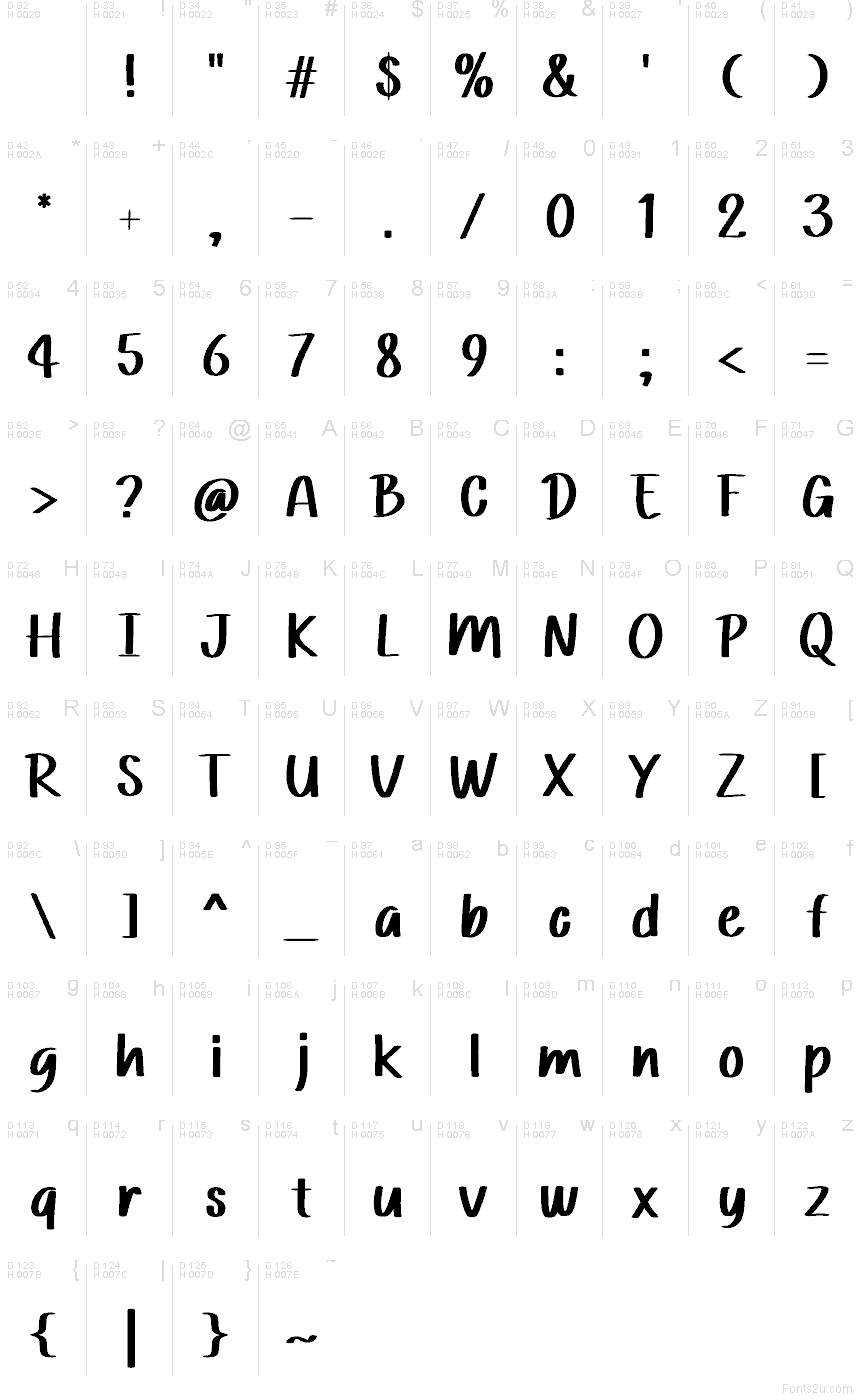
Border Wall від Hello Good Studio - це безкоштовний рукописний шрифт із високими, плавними штрихами та каллиграфічним характером. Літери вирізняються виразним контрастом між широкими вигинами та тонкими з'єднаннями, а м'які, округлі форми надають тексту природного, ритмічного вигляду.
Border Wall чудово підходить для створення логотипів, заголовків на плакатах, пакування, графіки з цитатами та редакційних акцентів, де потрібен рукописний стиль із більш витонченим, а не повсякденним настроєм. Цей безкоштовний шрифт також ідеально впишеться в айдентику кафе, запрошення та заголовки в соціальних мережах, оскільки його динамічні форми створюють відчуття руху, зберігаючи при цьому чітку структуру.